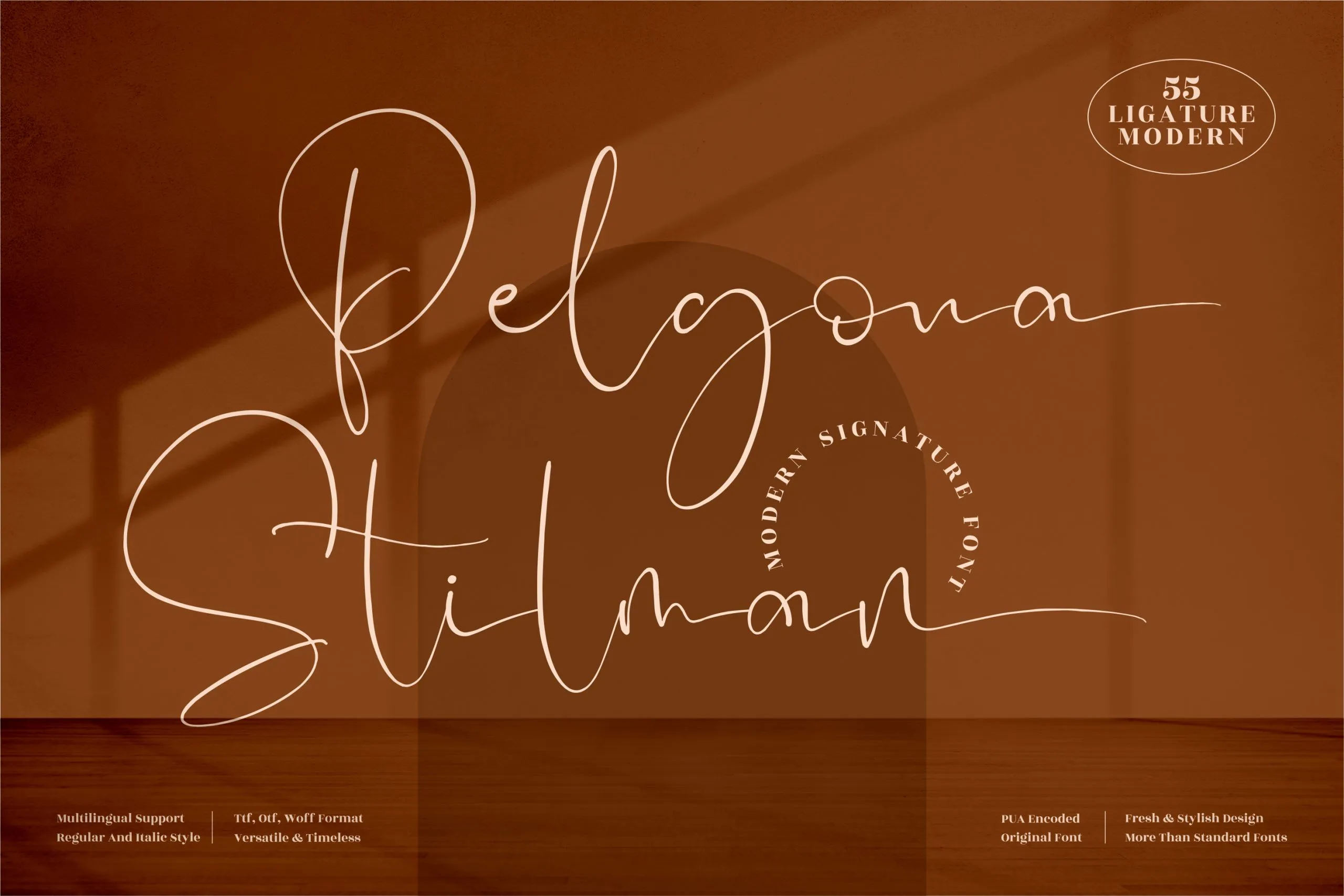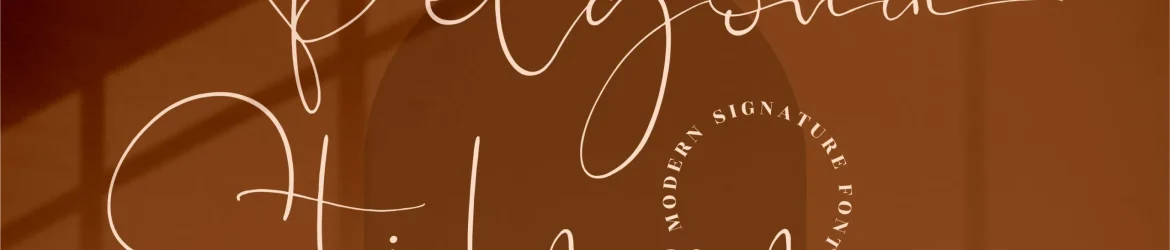
Pelgona Stilman Font – Download Grátis
A Pelgona Stilman Font é uma elegante e moderna fonte para assinatura, ideal para os projetos mais sofisticados do seu portfólio. Criada pela Perspectype Studio, essa fonte premium é perfeita tanto para criações gráficas como empreendimentos menos visuais, como capas de livros ou cartões de visita. Seu design fluido e arrojado se destaca especialmente em projetos que exigem uma assinatura única, como logotipos, embalagens, posteres e até mesmo em fotografias e peixes de água para eventos especiais. Ideal tanto para os mais modernos quanto para aqueles com um toque de elegância vintage, a Pelgona Stilman é uma escolha perfeita para qualquer projeto que exige um toque autêntico de sofisticação.